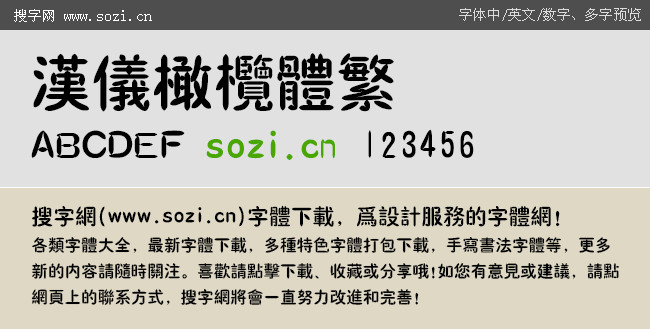
漢儀橄欖體繁
搜字網(wǎng)提供一款漢儀橄欖體POP藝術(shù)字體下載,漢儀橄欖體兩頭尖,中間呈凸圓弧形。筆畫簡(jiǎn)潔新穎,柔軟流暢,風(fēng)格稚氣質(zhì)樸,明快清純,藝術(shù)性較強(qiáng)。適合卡通畫冊(cè)、海報(bào)設(shè)計(jì)、包裝設(shè)計(jì)場(chǎng)合使用。